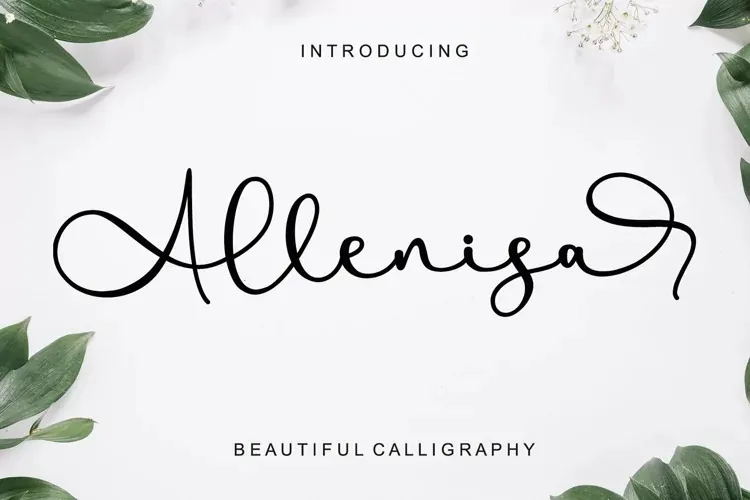
Allenisa Font – Download Grátis
A fonte Allenisa é uma elegante tipografia leve e manuscrita que oferece um toque único e impressiona com seu impacto. Ela traz letras fluidas que garantem um olhar singular e suave às suas criações, tornando-a ideal para uma variedade de projetos. Perfeita tanto para logotipos quanto para cartões de agradecimento, pacotes de design, identidade da marca ou mesmo para uma peça de arte DIY, ela também faz parte da seleção perfeita para títulos de livros, convites de casamento e embalagens. Seja qual seja o seu projeto, Allenisa trará um toque especial à sua obra. E como a fonte é do tipo script, certamente encaixará no seu estilo. Não deixe de experimentar esse belo recurso gráfico que pode revolucionar suas criações!